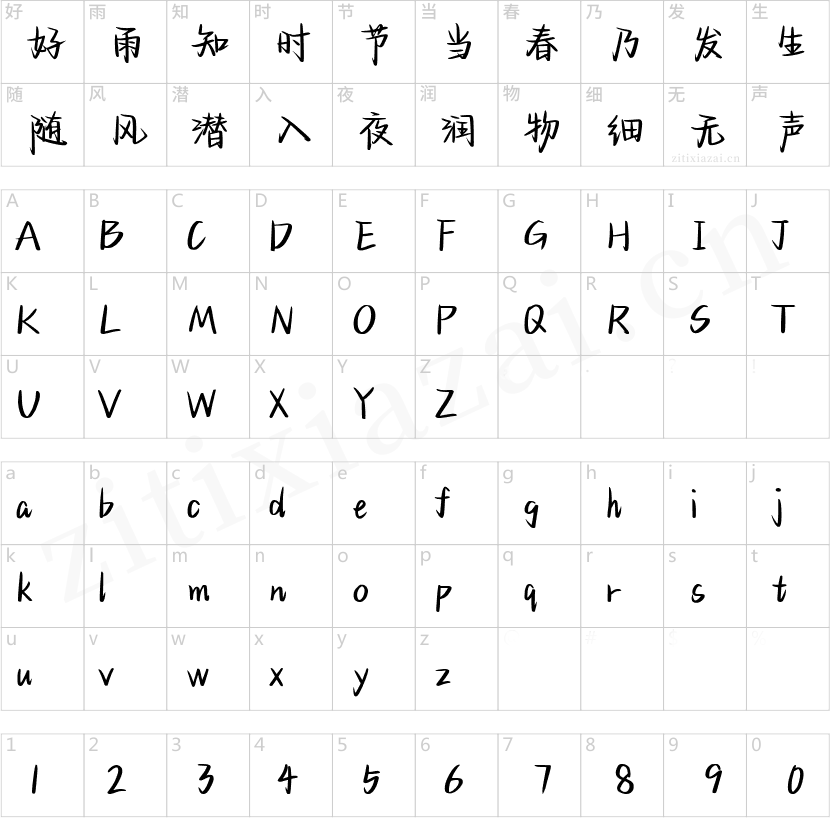
爱人的眼睛是第八大洋,这款字体结构工整、笔画清晰,兼顾美观与易读性,适用于标题、正文、海报、包装、LOGO 等多种场景。字形优雅稳定,风格百搭耐看,适配日常排版与创意设计,让文字呈现更舒适、更具质感。爱人的眼睛是第八大洋一笔一画,皆是细节,以均衡的比例、流畅的线条打造舒适视觉体验,字形端正大气,风格简约现代。无论是商业设计、品牌宣传还是日常排版,都能轻松驾驭,让文字更有格调与力量。爱人的眼睛是第八大洋字体下载。
爱人的眼睛是第八大洋字体
爱人的眼睛是第八大洋是一款非常具有艺术性的字体,它的设计灵感来源于对古典艺术的研究,同时又融入了现代字体设计的元素。字形优美,笔画粗细变化自然,给人以大气、典雅的感觉。爱人的眼睛是第八大洋是一款既传统又现代的字体,它的设计充满艺术感,美观大方,实用性也非常强。无论是对于设计师还是对于普通读者来说,都是一种非常不错的字体选择。爱人的眼睛是第八大洋适合用于具有艺术感的场合,比如海报、宣传单张、书籍封面等。由于其字形流畅且具有动态感,也适合用于大量的文本排版,如报纸、杂志等。